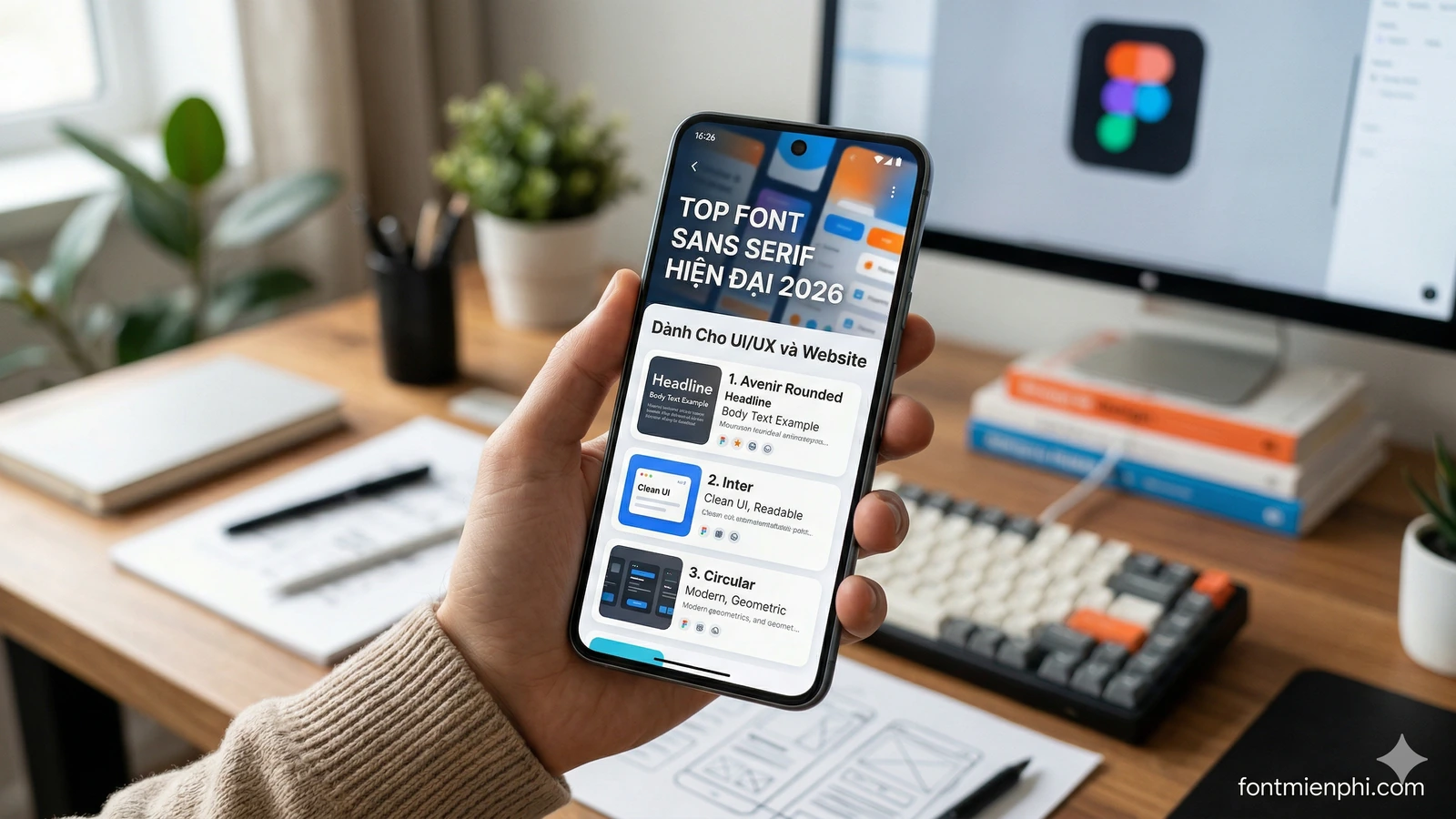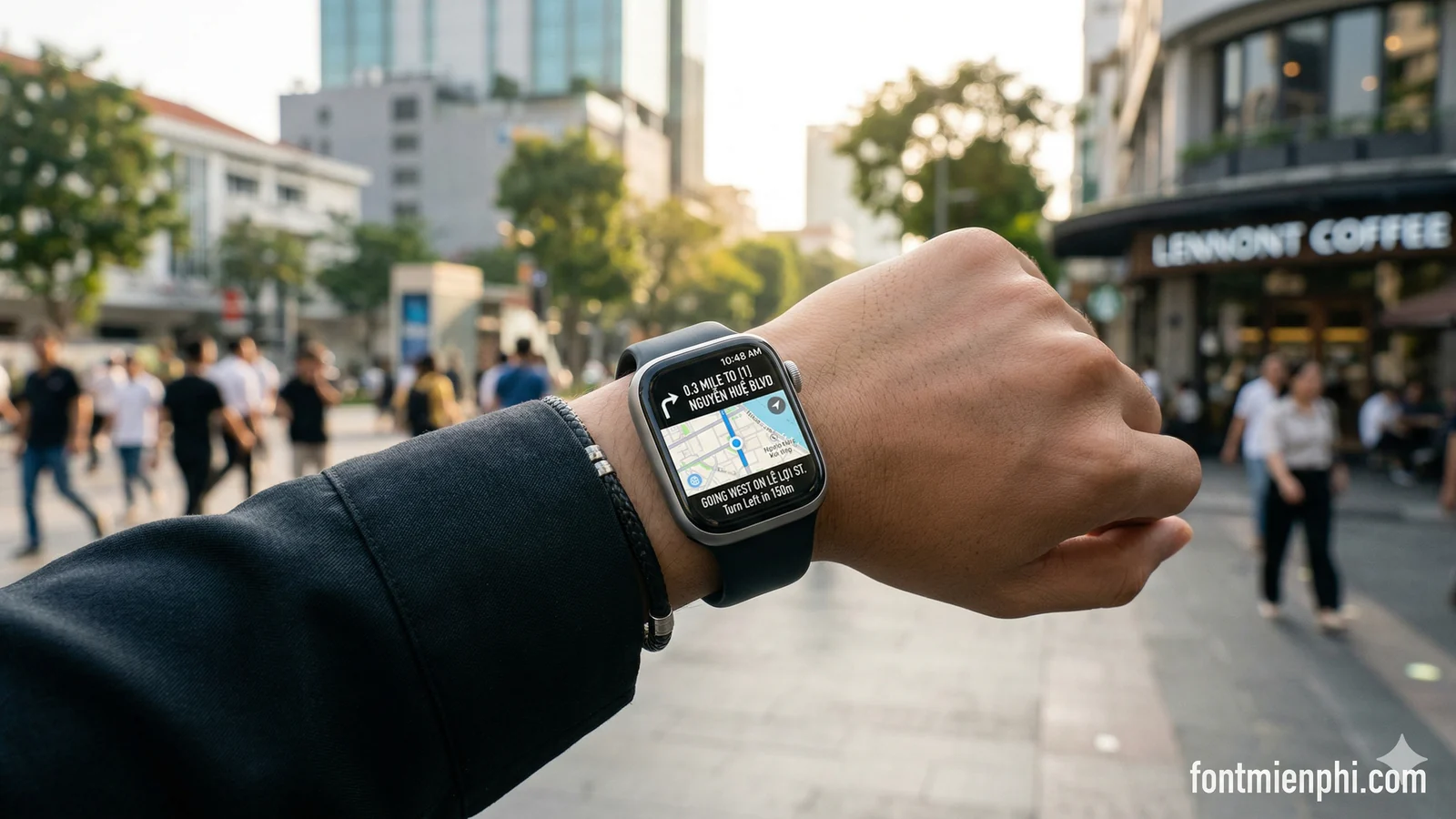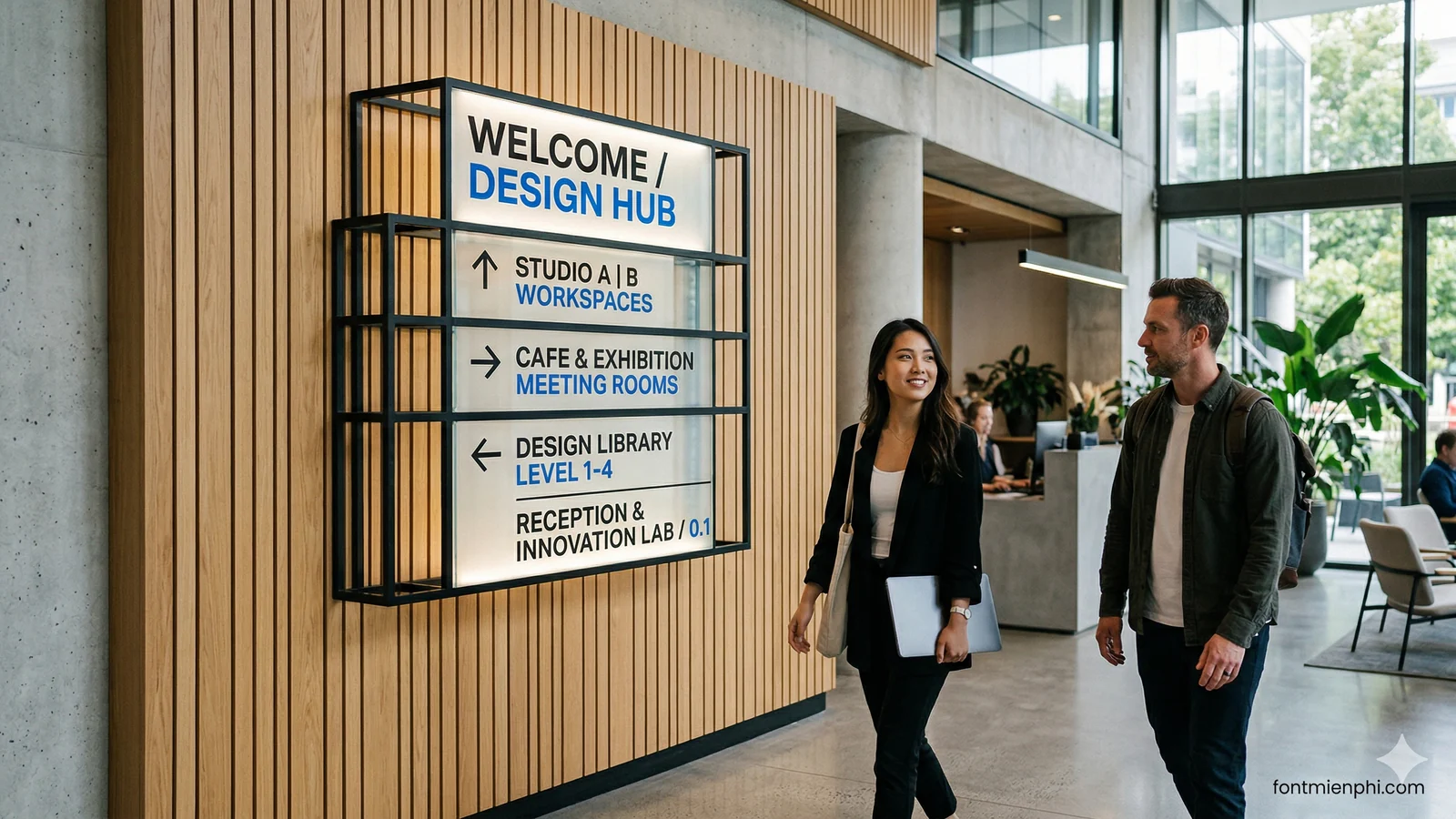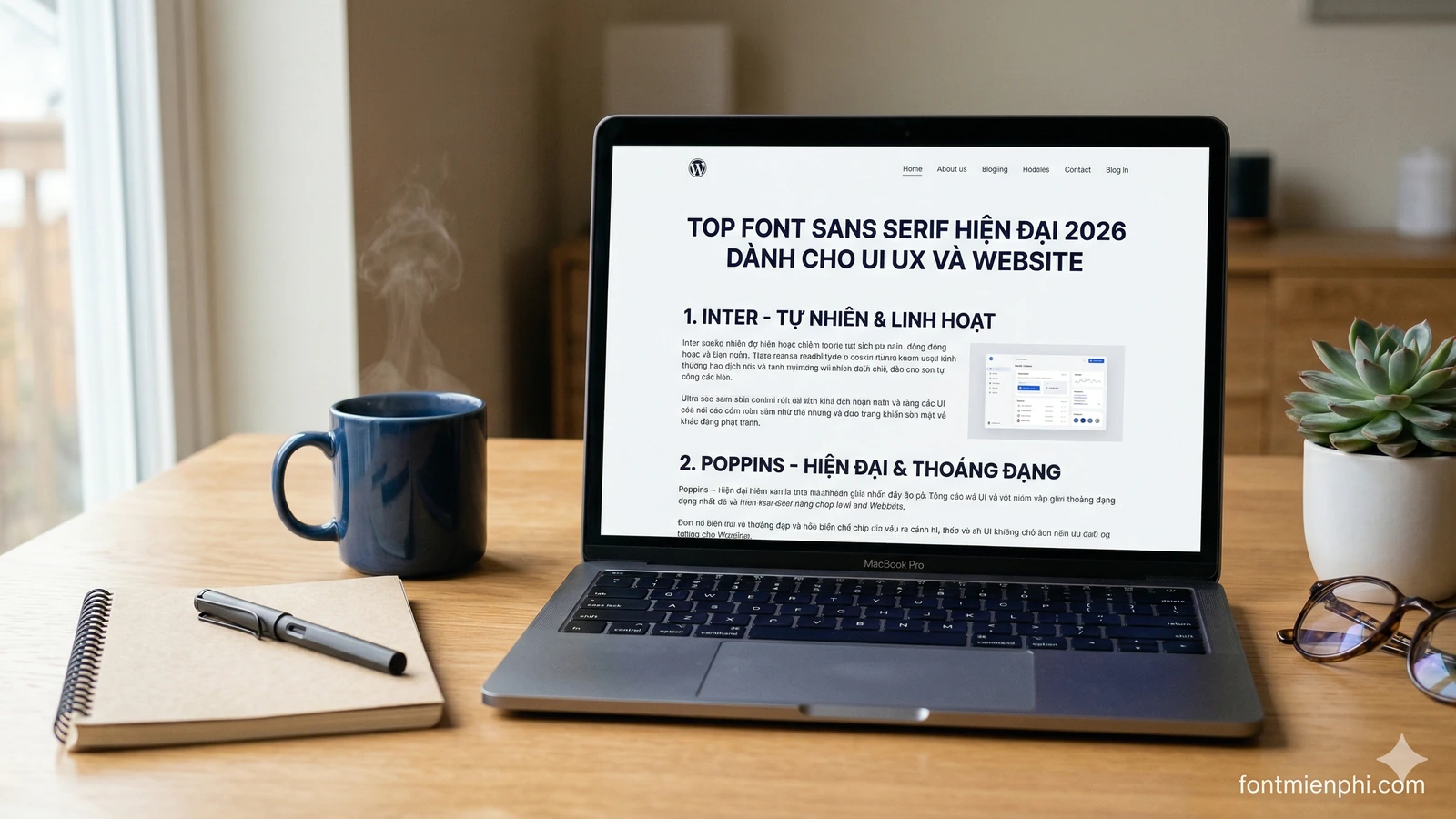
Top Font Sans Serif Hiện Đại 2026 Dành Cho UI UX Và Website
Trong bối cảnh thiết kế kỹ thuật số năm 2026, việc lựa chọn phông chữ không chỉ dừng lại ở tính thẩm mỹ mà còn là yếu tố then chốt quyết định trải nghiệm người dùng và hiệu suất chuyển đổi. Bài viết này tổng hợp những bộ font Sans Serif hiện đại nhất, tối ưu riêng cho giao diện UI UX và website, giúp các nhà thiết kế xây dựng hệ thống phân cấp thị giác chuyên nghiệp và mạch lạc.
Top Font Sans Serif Hiện Đại 2026 Dành Cho UI UX Và Website
Sự tiến hóa của màn hình hiển thị với độ phân giải siêu cao trong năm 2026 đã thúc đẩy các nhà thiết kế chữ tạo ra những bộ font Sans Serif có độ sắc nét tối đa. Một bộ font tốt hiện nay phải đáp ứng được khả năng đọc tốt trên các thiết bị đeo thông minh, màn hình thực tế ảo lẫn các trình duyệt web truyền thống.
Tầm quan trọng của Sans Serif trong thiết kế hiện đại
Sans Serif, hay font chữ không chân, từ lâu đã trở thành tiêu chuẩn vàng cho các nền tảng kỹ thuật số. Khác với các dòng Serif có chân mảnh dễ bị mờ trên màn hình độ phân giải thấp, Sans Serif giữ được cấu trúc hình học sạch sẽ, giúp mắt người dùng ít điều tiết hơn khi đọc nội dung dài.
Tính linh hoạt: Sans Serif có thể thích nghi với nhiều phong cách từ tối giản, sang trọng đến năng động, trẻ trung.
Hiệu suất tải trang: Các biến thể font (Variable Fonts) hiện đại giúp giảm dung lượng tệp tin, tăng tốc độ phản hồi của website.
Khả năng tiếp cận: Độ tương phản giữa các nét chữ và khoảng trống bên trong (counter) giúp người khiếm thị hoặc người có thị lực kém dễ dàng tiếp nhận thông tin.
Tiêu chí lựa chọn font chữ cho UI UX năm 2026
Để một bộ font được coi là phù hợp cho dự án năm 2026, nó cần trải qua các bài kiểm tra nghiêm ngặt về kỹ thuật và thẩm mỹ.
Hỗ trợ đa ngôn ngữ: Đặc biệt là các ký tự có dấu trong tiếng Việt cần được thiết kế tỉ mỉ, không bị lỗi nhảy dòng hay sai lệch cao độ.
Hệ sinh thái Variable Font: Cho phép điều chỉnh trọng lượng (weight), độ rộng (width) và độ nghiêng (slant) một cách mượt mà chỉ với một tệp tin duy nhất.
Tính dễ đọc ở kích thước nhỏ: Các ký tự như i, l, 1 hoặc o, 0 cần có sự phân biệt rõ ràng để tránh gây nhầm lẫn trong các giao diện điều hướng phức tạp.
Danh sách các font Sans Serif hàng đầu cho Website
Dưới đây là những lựa chọn ưu việt nhất được các chuyên gia UI UX tin dùng trong năm 2026.
1. Inter – Tiêu chuẩn vàng cho ứng dụng web
Inter tiếp tục khẳng định vị thế là bộ font Sans Serif phổ biến nhất thế giới cho các giao diện người dùng. Được thiết kế đặc biệt cho màn hình máy tính, Inter có chiều cao chữ cái thường (x-height) lớn, giúp văn bản cực kỳ dễ đọc ngay cả ở kích thước 10px.
Đặc điểm: Cấu trúc hình học pha trộn với các nét nhân văn, tạo cảm giác tin cậy nhưng không quá cứng nhắc.
Ứng dụng: Phù hợp cho bảng điều khiển (dashboard), hệ thống quản trị dữ liệu và các trang tin tức chuyên sâu.
2. Plus Jakarta Sans – Luồng gió mới từ Đông Nam Á
Đây là một bộ font hiện đại mang phong cách hình học (geometric) rất mạnh mẽ. Plus Jakarta Sans mang lại cảm giác sạch sẽ, hiện đại và vô cùng phóng khoáng.
Đặc điểm: Các vòng tròn trong chữ cái được thiết kế gần như hoàn hảo, tạo sự cân bằng thị giác tuyệt vời.
Ứng dụng: Rất tốt cho các trang landing page công nghệ, startup hoặc các ứng dụng di động dành cho giới trẻ.
3. Satoshi – Sự tinh tế trong từng đường nét
Satoshi kết hợp giữa các nguyên tắc thiết kế cổ điển và hiện đại. Đây là bộ font có độ tương phản nét thanh nét đậm rất nhẹ nhàng, tạo nên vẻ ngoài sang trọng.
Đặc điểm: Hệ thống ký tự thay thế (alternates) phong phú, cho phép nhà thiết kế tùy biến logo hoặc tiêu đề một cách độc đáo.
Ứng dụng: Thích hợp cho các website thời trang cao cấp, kiến trúc hoặc blog cá nhân mang phong cách tối giản.
Xu hướng sử dụng font Sans Serif trong trải nghiệm người dùng
Năm 2026 chứng kiến sự lên ngôi của phong cách Micro-typography. Các nhà thiết kế không chỉ chọn font mà còn can thiệp sâu vào khoảng cách dòng (line-height) và khoảng cách chữ (letter-spacing) để tối ưu hóa khả năng quét nội dung của người dùng.
Sử dụng Variable Fonts để tối ưu hiệu năng
Thay vì phải tải 5 đến 7 tệp font khác nhau cho các định dạng in đậm, in nghiêng, nhà thiết kế hiện nay chỉ sử dụng một tệp Variable Font duy nhất. Điều này giúp:
Giảm số lượng yêu cầu HTTP, từ đó tăng điểm số Core Web Vitals của Google.
Tạo ra các hiệu ứng chuyển cảnh (animation) mượt mà cho chữ cái khi người dùng di chuột hoặc cuộn trang.
Tự động điều chỉnh trọng lượng chữ dựa trên điều kiện ánh sáng môi trường của thiết bị người dùng.
Kết hợp cặp font (Font Pairing) hiệu quả
Một xu hướng phổ biến trong năm 2026 là sử dụng cùng một họ font Sans Serif nhưng khác biệt về trọng lượng cho tiêu đề và nội dung chính.
Tiêu đề (Headings): Sử dụng các biến thể Bold hoặc Black để tạo điểm nhấn thị giác mạnh mẽ.
Phản hồi từ người dùng: Thực hiện các bài kiểm tra A/B testing với hai bộ font khác nhau để xem bộ nào mang lại tỷ lệ chuyển đổi hoặc thời gian đọc trang tốt hơn.
Sự phát triển của công nghệ hiển thị và tư duy thiết kế lấy người dùng làm trung tâm đã biến việc chọn font thành một bộ môn khoa học chính xác. Những bộ font Sans Serif hiện đại của năm 2026 không chỉ đơn thuần là công cụ truyền tải văn bản, mà còn là linh hồn của giao diện kỹ thuật số, giúp kết nối thương hiệu với người dùng một cách tự nhiên và hiệu quả nhất qua từng điểm chạm trên màn hình.